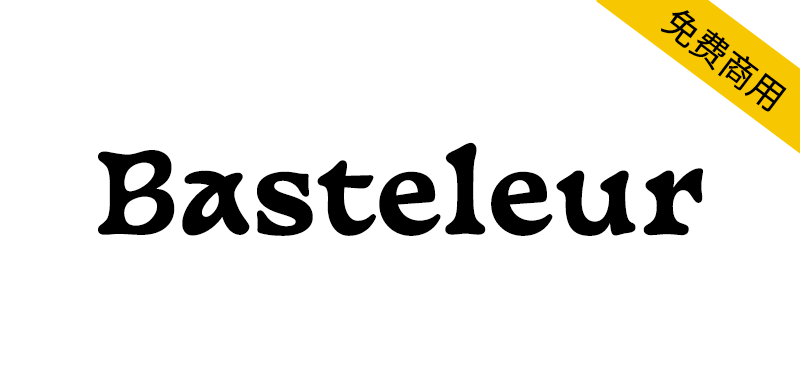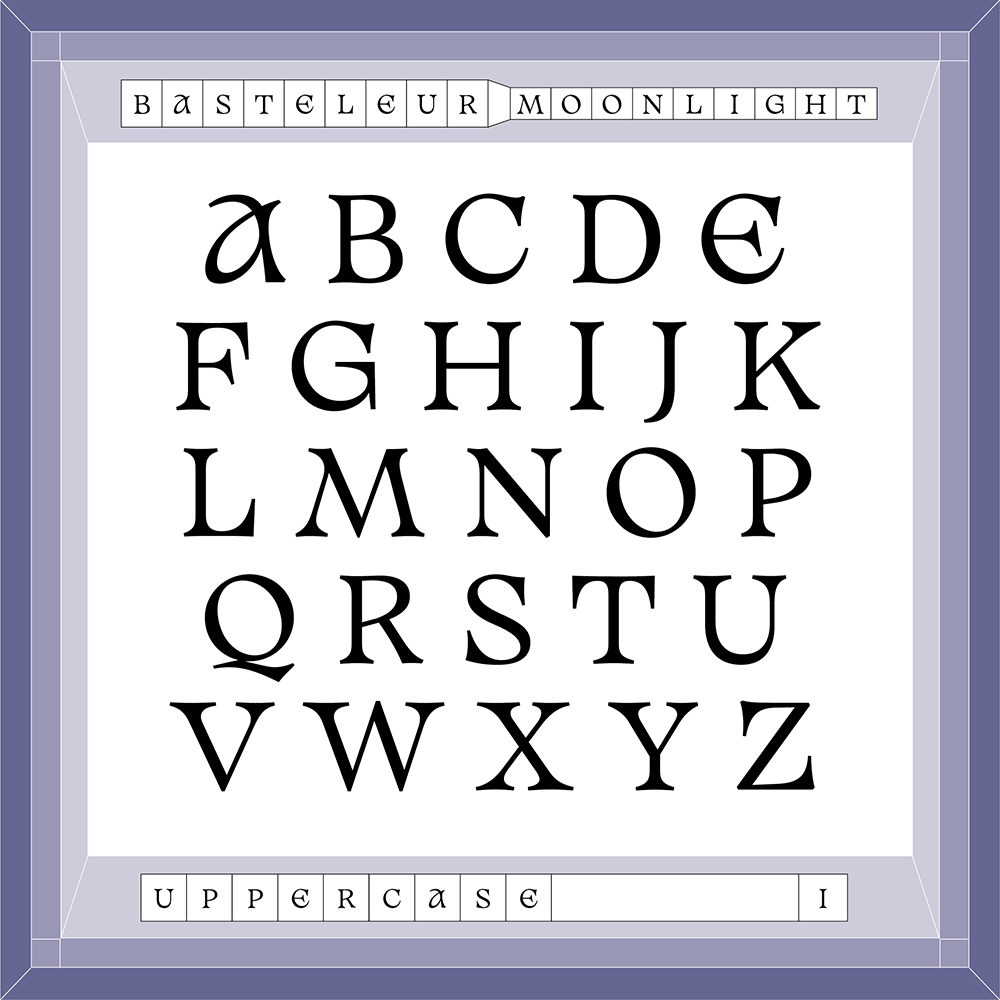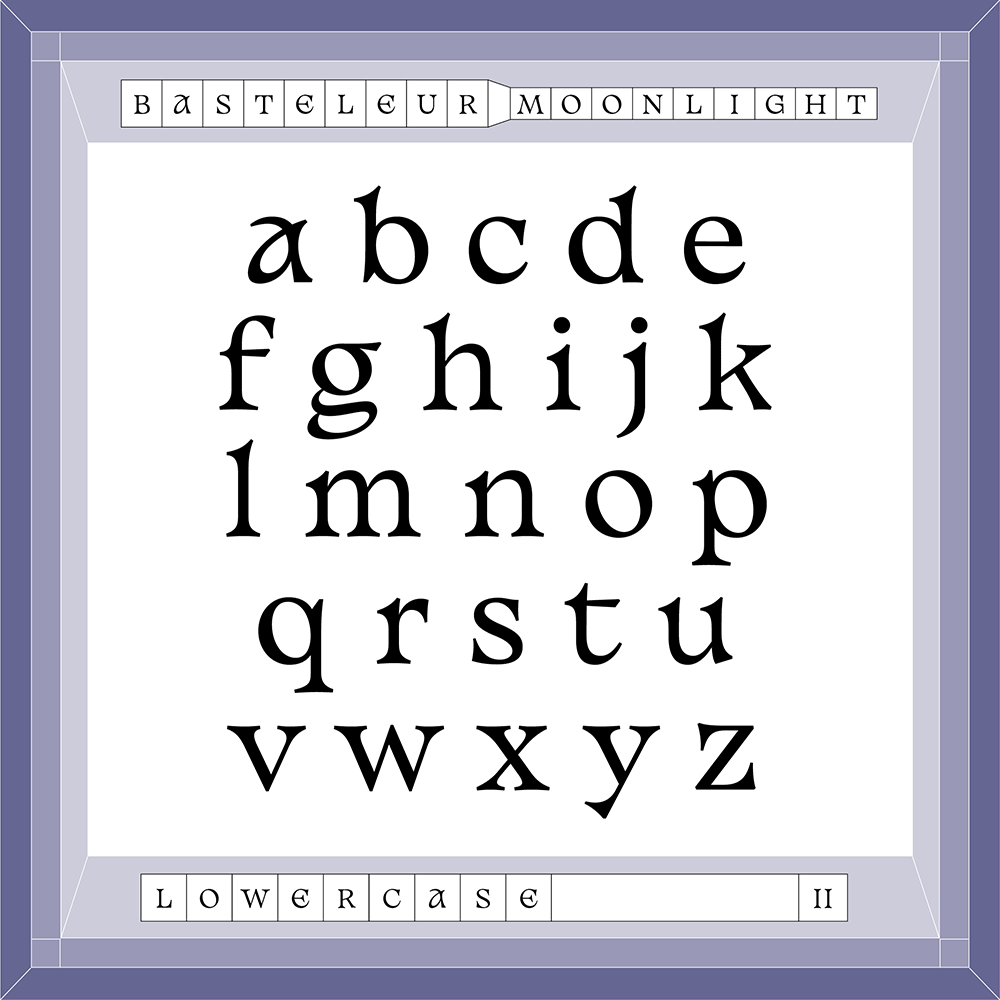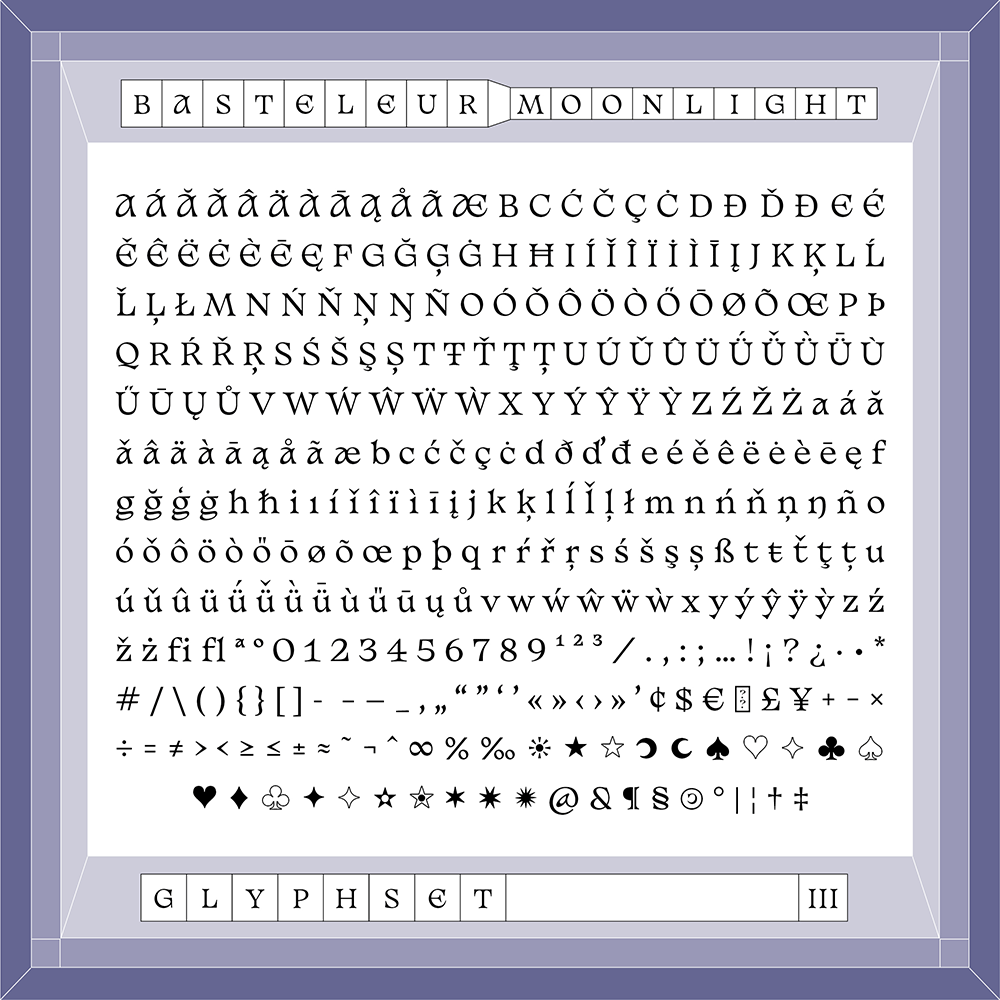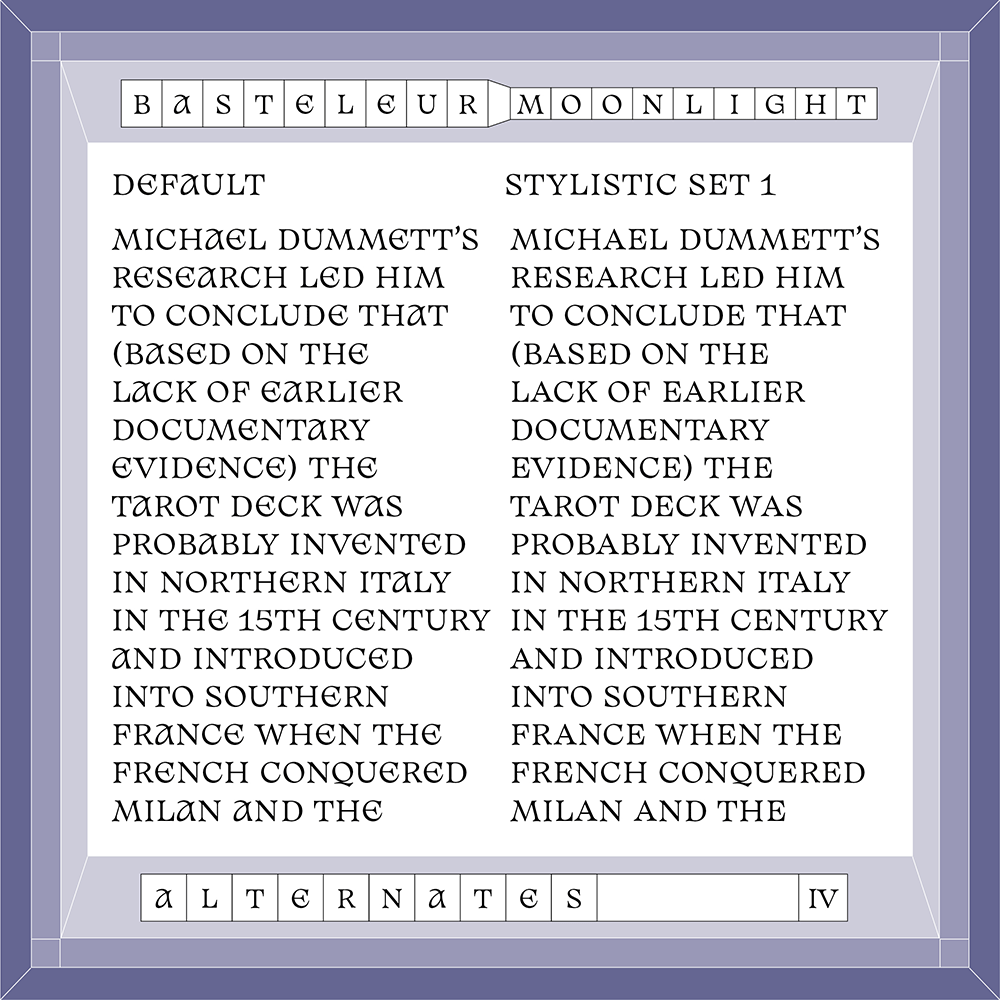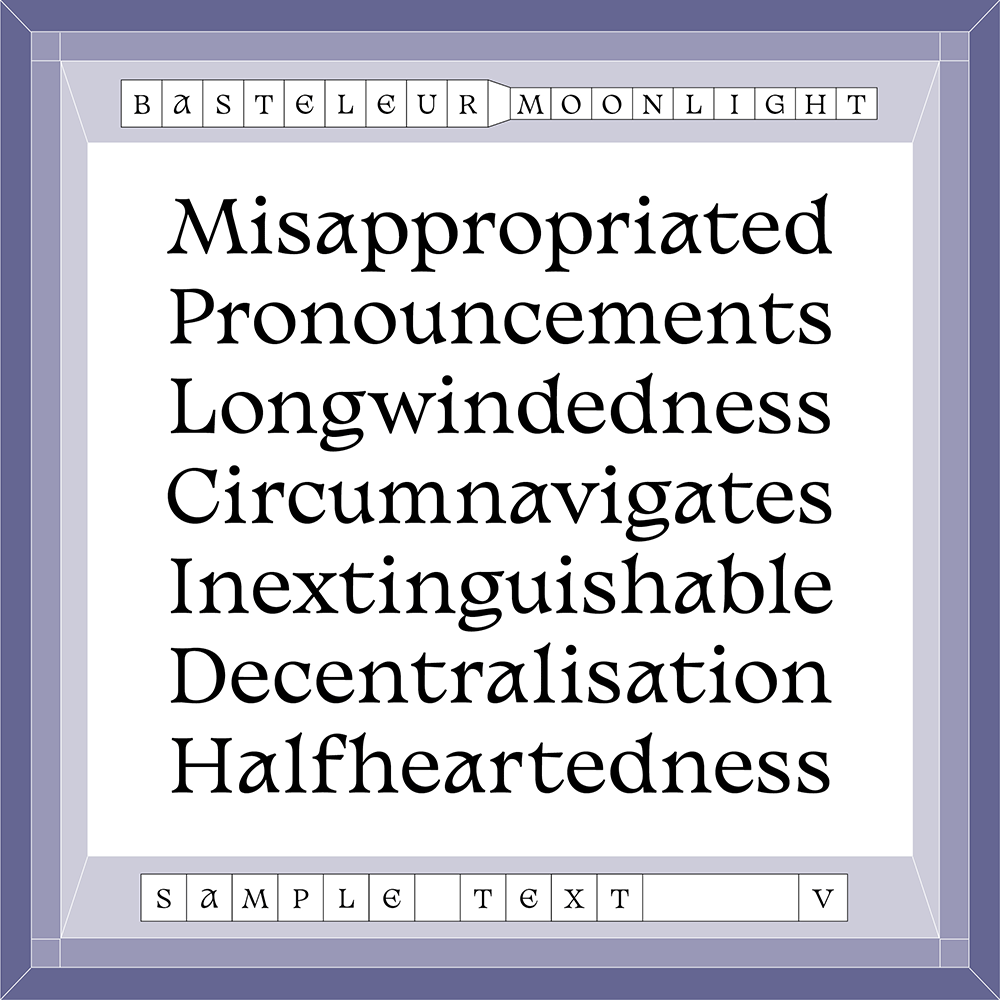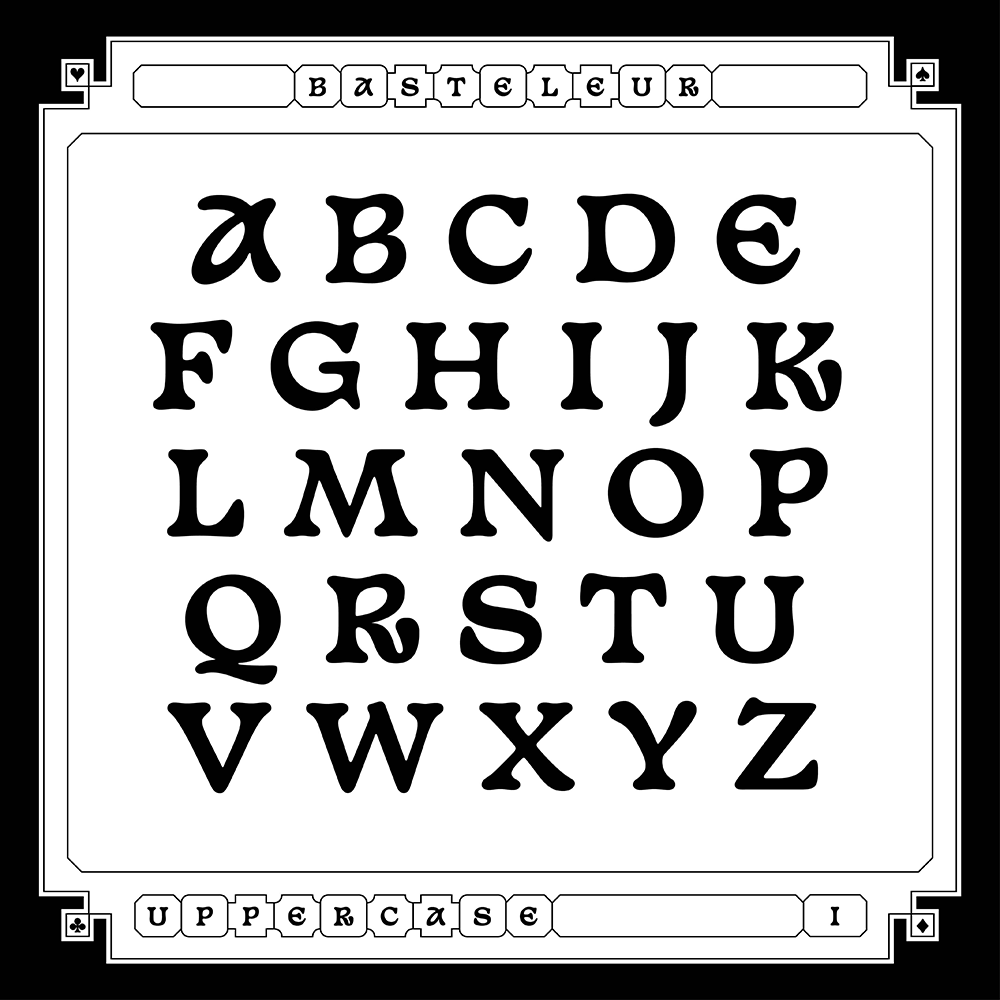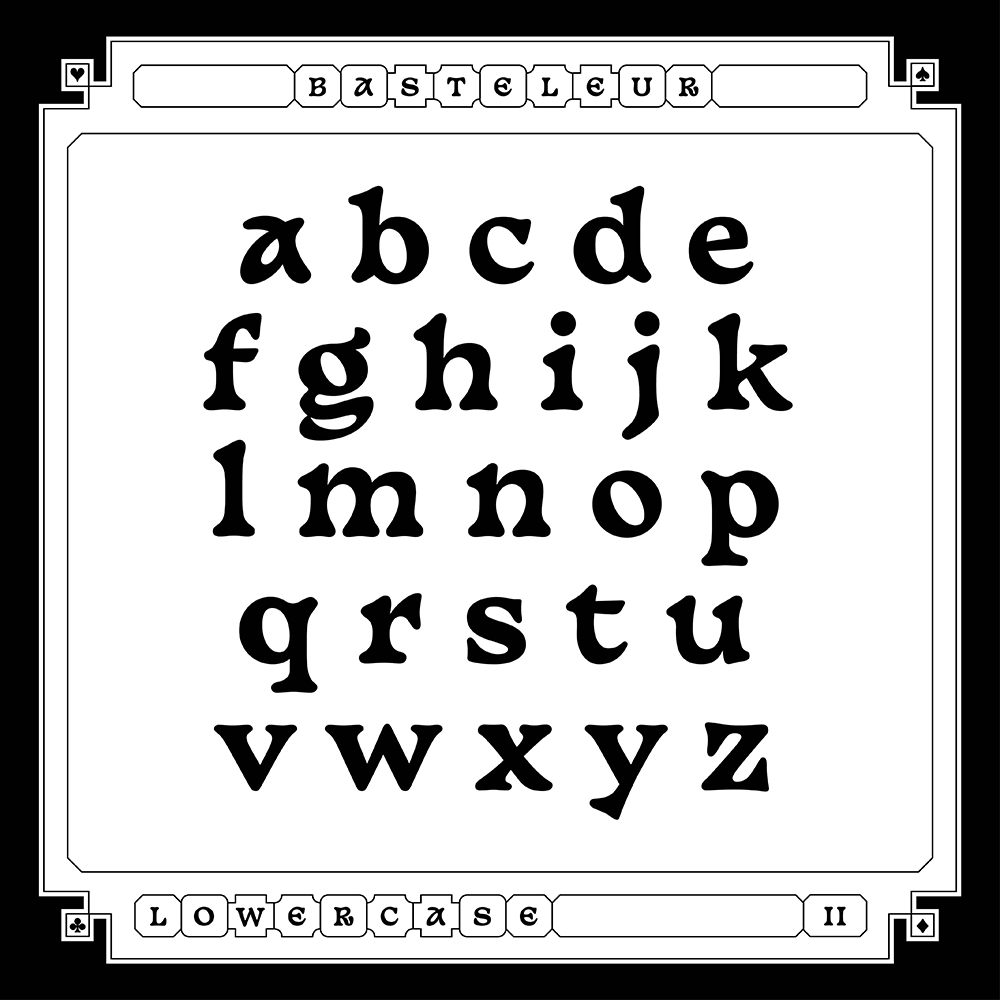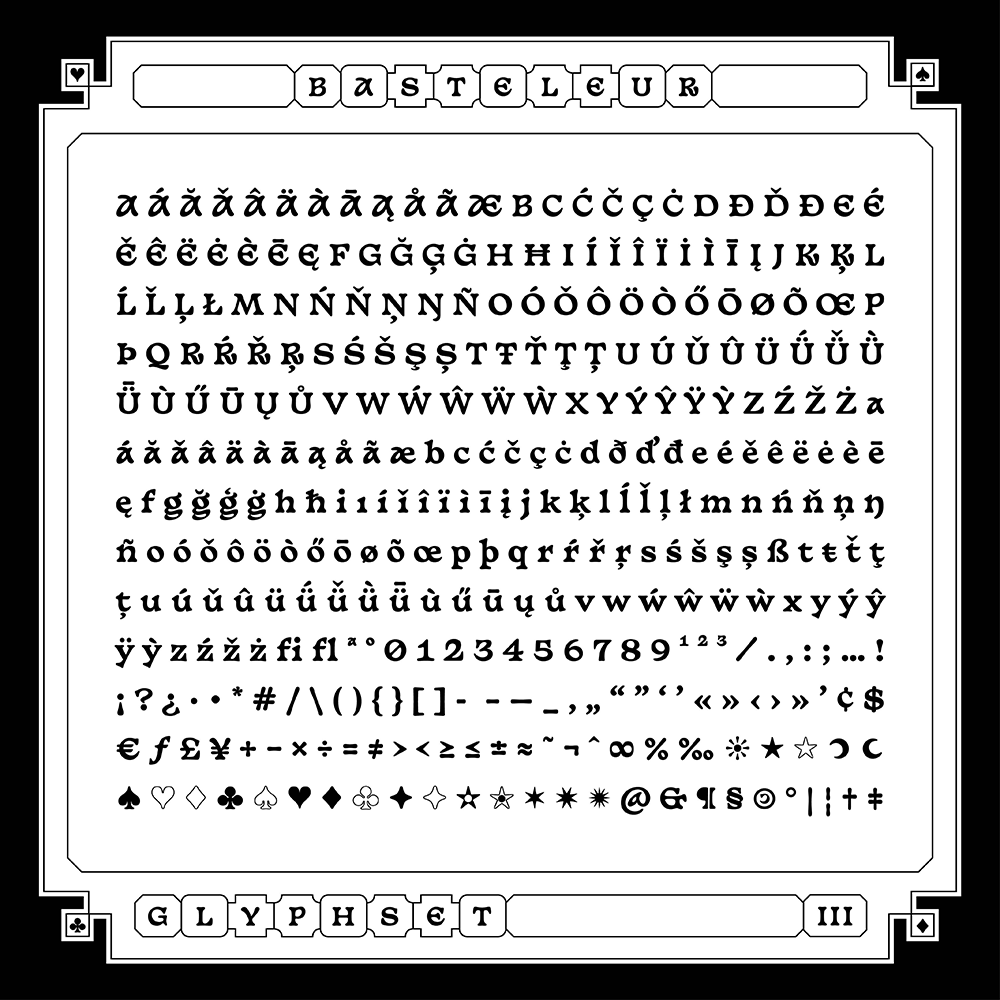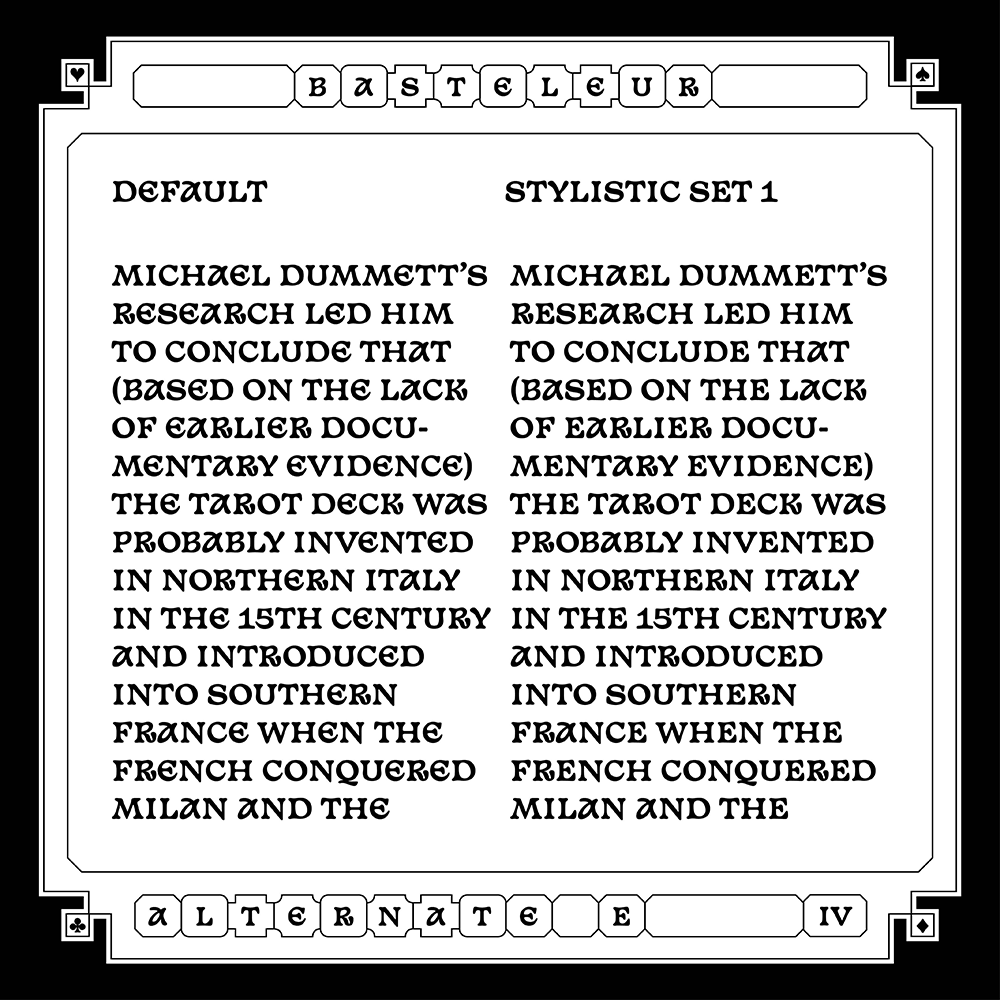
【Basteleur】有趣的混合了中世纪风格和铜黑色风格的字体
中世纪神秘与铜黑色风格的奇妙碰撞!Basteleur字体源于马赛塔罗牌,不仅呈现独特视觉美学,更暗喻设计师的创作历程:新开始、乐趣与挑战并存。2022年更新后,这款字体在粗犷柔和之外增添了轻盈清晰的新选择。更令人惊喜的是,它采用高自由度的开源授权,无论是个人项目还是商业应用,都能尽情挥洒创意,无需付费或署名。
【Basteleur】有趣的混合了中世纪风格和铜黑色风格的字体
Basteleur字体是在马赛塔罗牌的基础上设计的。这就产生了一种有趣的混合了中世纪风格和铜黑色风格的字体。2022年6月的周年更新在原来粗犷柔和的基础上增加了更轻、更清晰的字重。
Basteleur Arcana代表了设计师能够体验到的许多内容:全新的开始,乐趣,制作,但也包括缺乏自信以及难以完成项目。
This typeface was designed with the Tarot de Marseille in mind. This led to a funny blend of medieval-ish and cooperblack-ish typeface. An anniversary update of June 2022 adds a lighter and sharper weight to the original bold and soft one.
The Basteleur Arcana represents a lot of things a designer can experience: new beginnings, having fun, crafting, but also a lack of confidence and having hard time to finish projects.